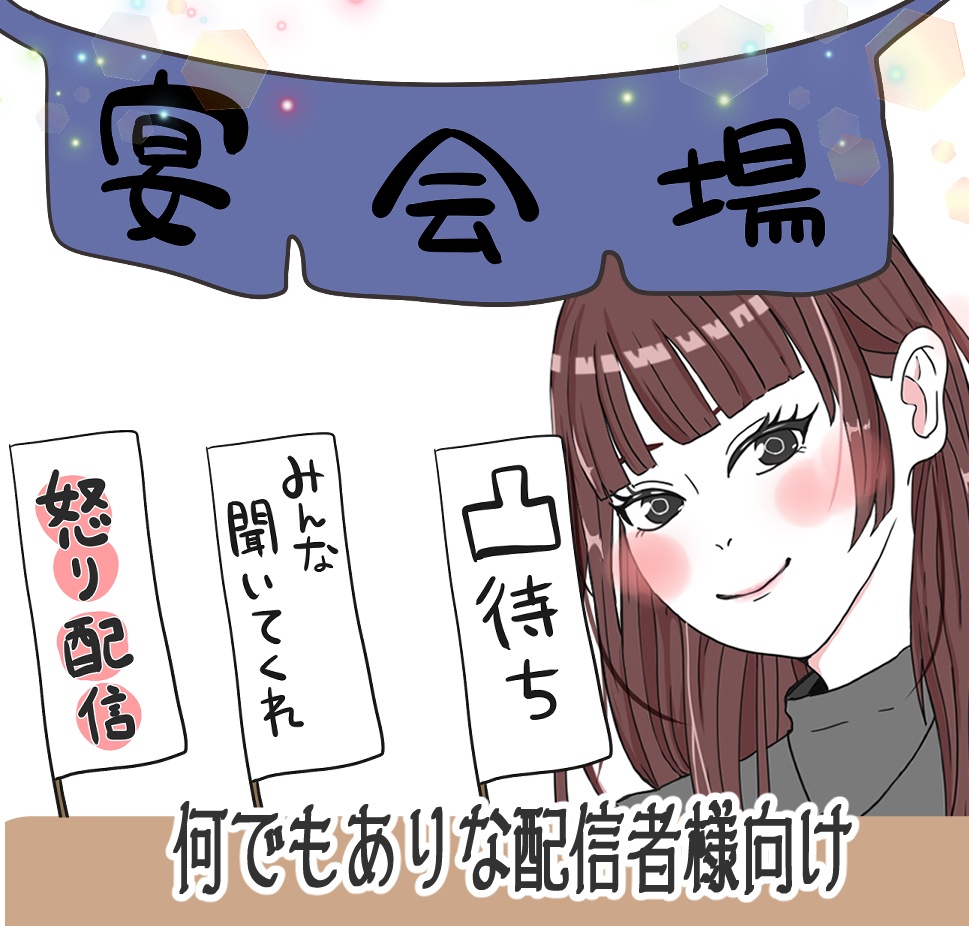
akiramoko配信素材・手描きフォントDigital100 JPY카트에 담기기프트 보내기About Gift可愛くてオシャレなだけじゃない! 個性派配信者様はこちらをお使いくださいませ! 他には無い手描きフォントです 配信画面に貼り付けてお使いください。 データ形式:PNG よろしくお願い致しますakiramokoVisit FANBOX!Stickers騒がしい素直な猫のステッカーakiramoko770 JPYStickers素直な猫のステッカーakiramoko770 JPYT-Shirtsやるなら今しかねぇ猫akiramoko1,750 JPYAcrylic Keychains素直な猫のアクキーakiramoko880 JPYAcrylic Keychains騒がしい素直な猫akiramoko1,060 JPYFonts手描きフォント・文字素材詰め合わせ・配信や配布物にakiramoko100 JPYIllustration (Other)歯科衛生士・イラスト詰め合わせakiramoko100 JPYFonts手描きフォント・文字素材詰め合わせ・配信や配布物にakiramoko100 JPYFonts手書きフォント・文字素材詰め合わせakiramoko100 JPYGlasses & Tumblers & Mugsクロネコマグakiramoko1,750 JPYAcrylic Keychainsクロネコチャンakiramoko880 JPYIllustration (Other)手書き文字・文字素材詰め合わせakiramoko100 JPYFonts手書きフォント・文字素材詰め合わせakiramoko100 JPYMaterials (Other)配信用素材・ビスケットakiramoko100 JPYIllustration (Other)スケジュールメモ帳akiramoko0 JPYBackground Images背景画像・星空akiramoko0 JPYMaterials (Other)背景素材集akiramoko100 JPY~Photos【配信画面】写真立て12種・推し色akiramoko100 JPYIllustration (Other)歯科衛生士・歯科助手イラストakiramoko100 JPYGraphics【配信】花瓶・観葉植物セット【VTuber】akiramoko100 JPY더보기